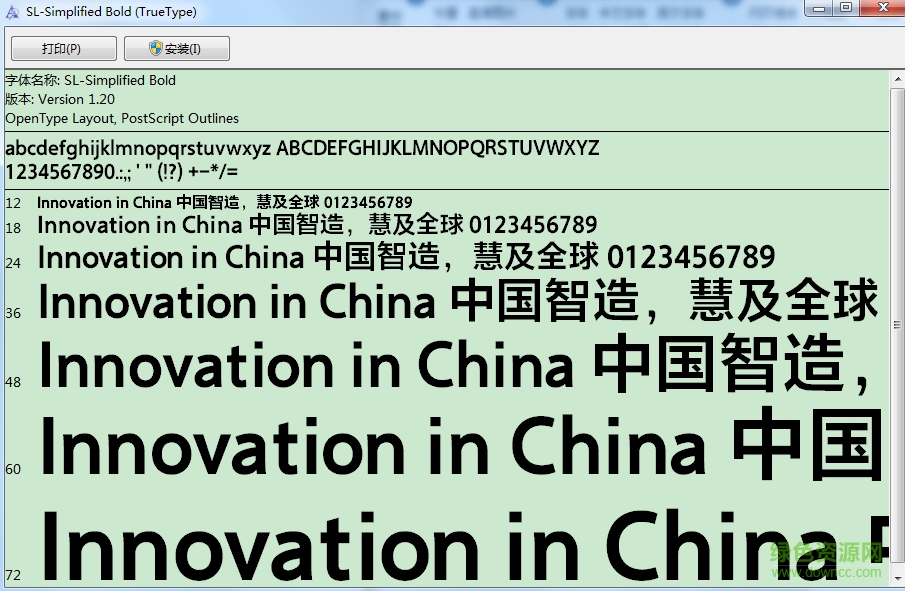
索尼蘭亭黑ttf字體是一款常用的黑體字體,這款字體端正大方,筆畫(huà)粗壯,給人一種厚實(shí)感,非常適用于廣告設(shè)計(jì)、排版印刷等領(lǐng)域,需要的朋友歡迎來(lái)綠色資源網(wǎng)免費(fèi)下載使用。
索尼蘭亭黑ttf字體,沒(méi)有襯線(xiàn)裝飾,筆劃粗壯有力,撇捺等筆畫(huà)不尖,使人易於閱讀。喜歡的朋友歡迎來(lái)綠色資源網(wǎng)下載使用。